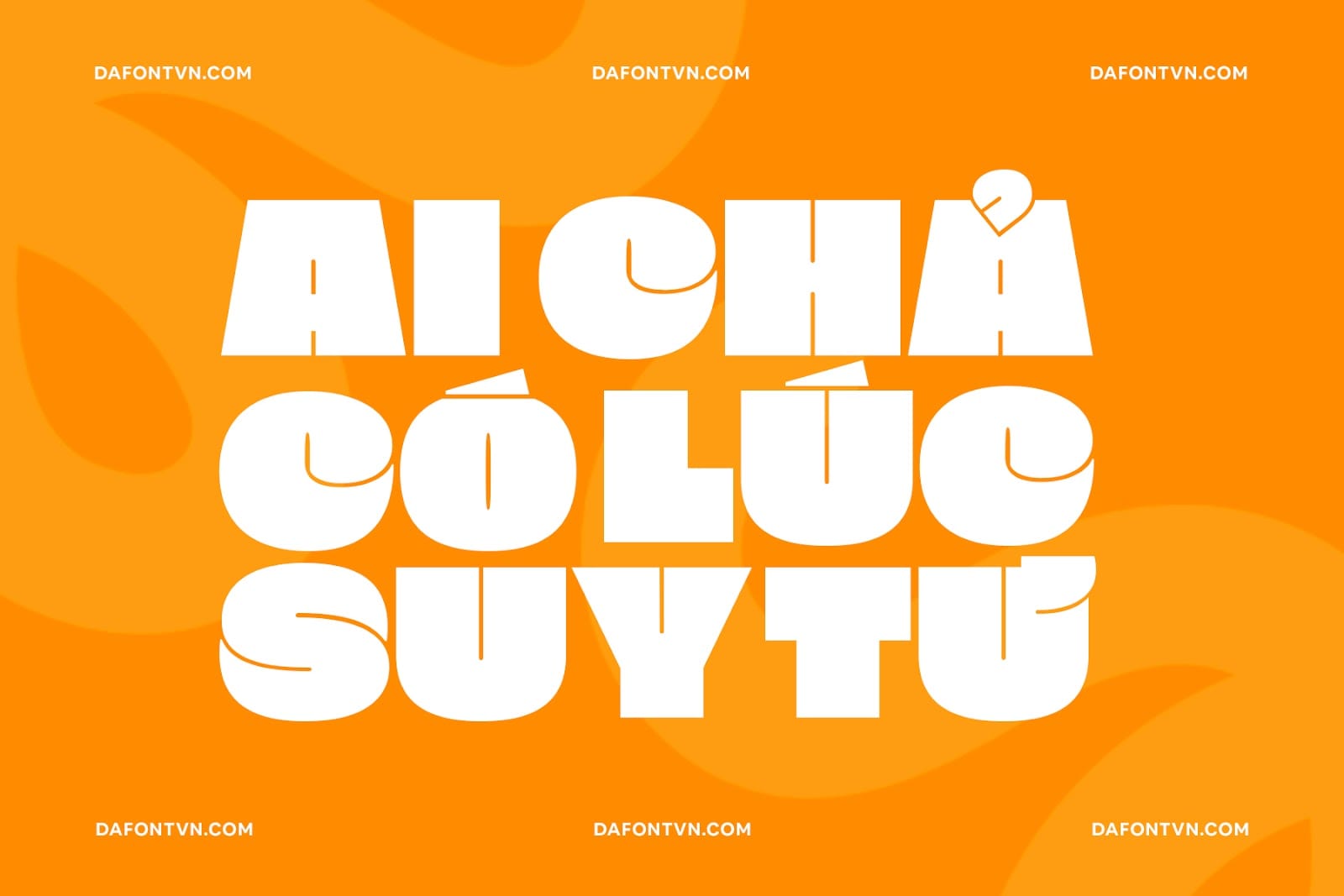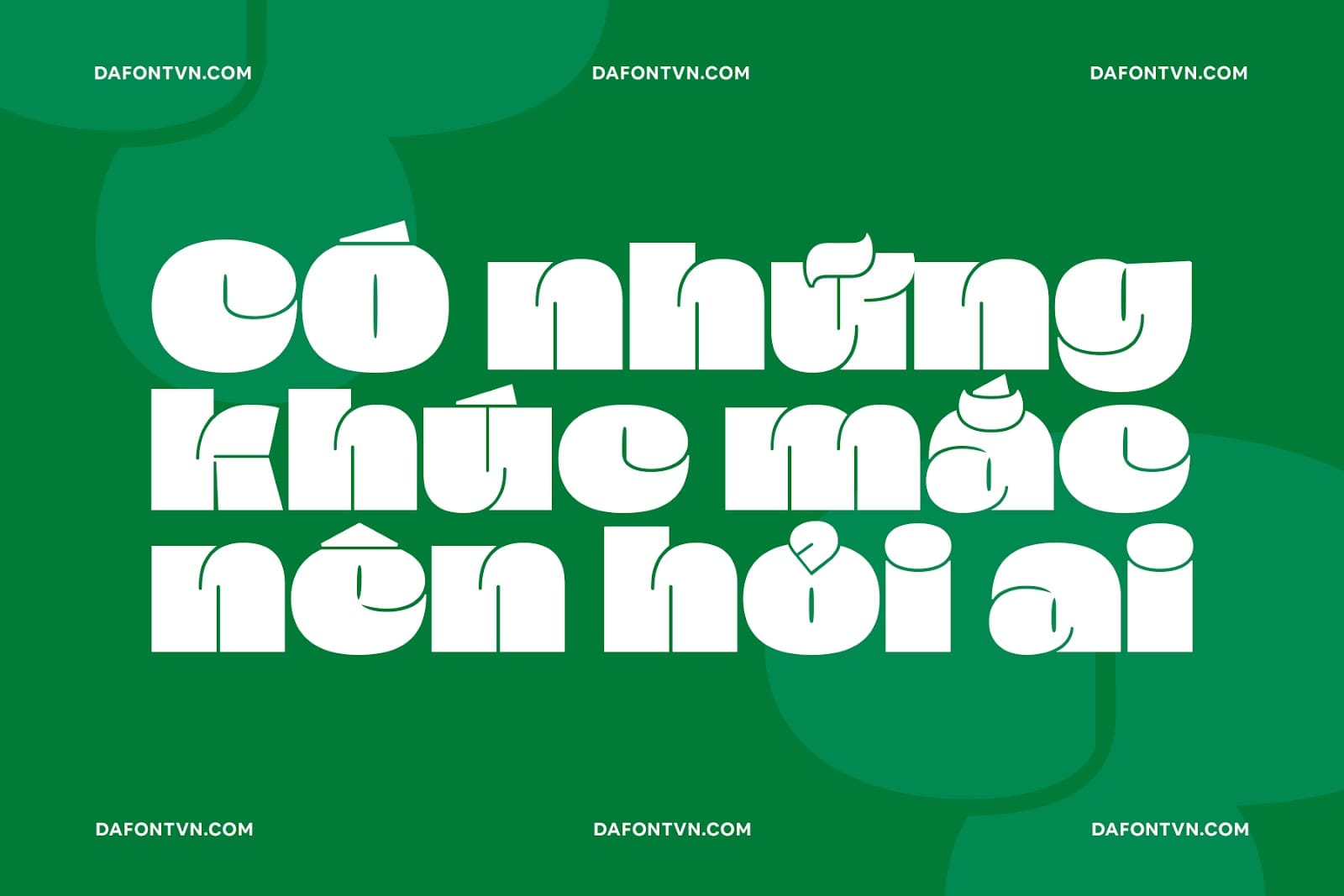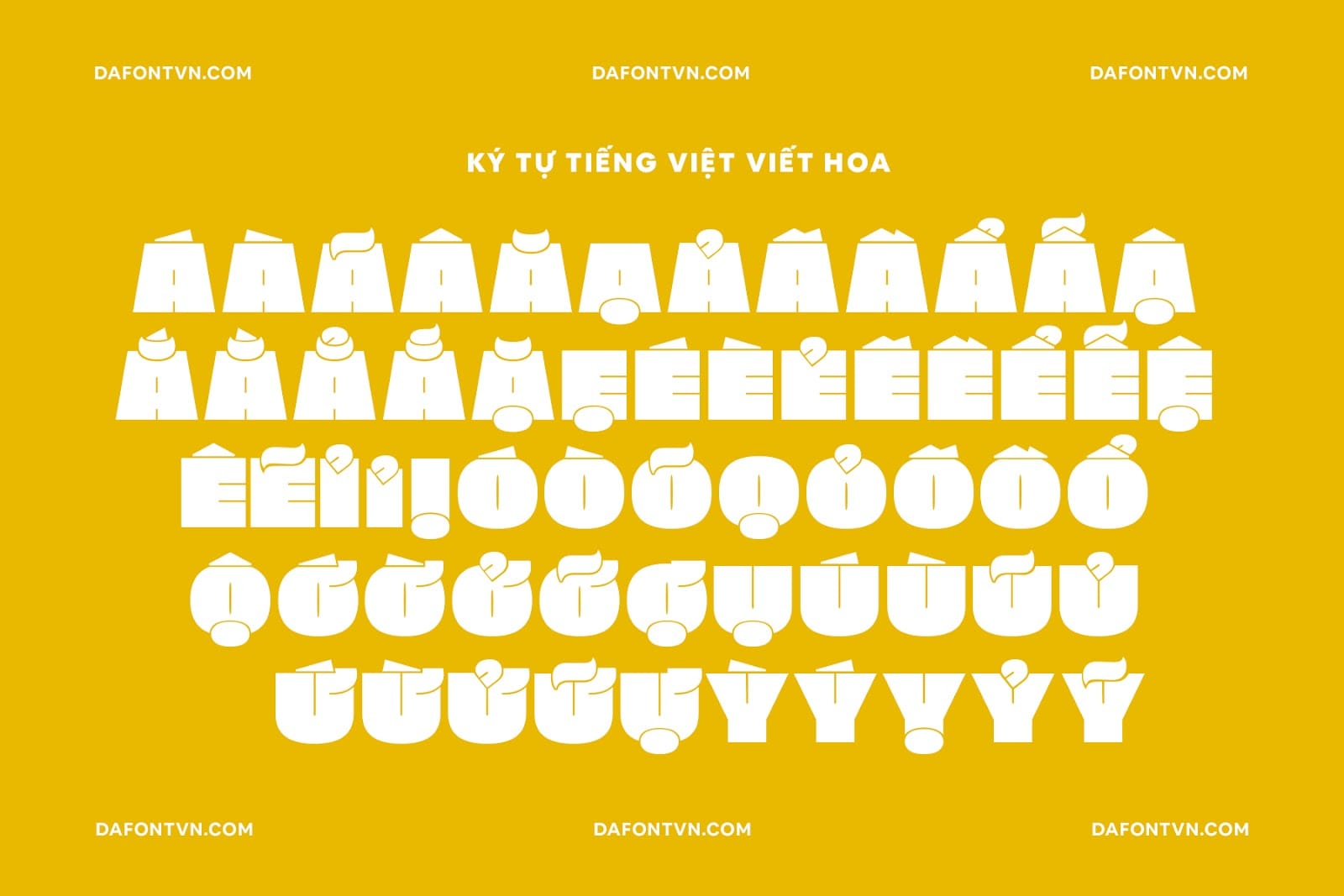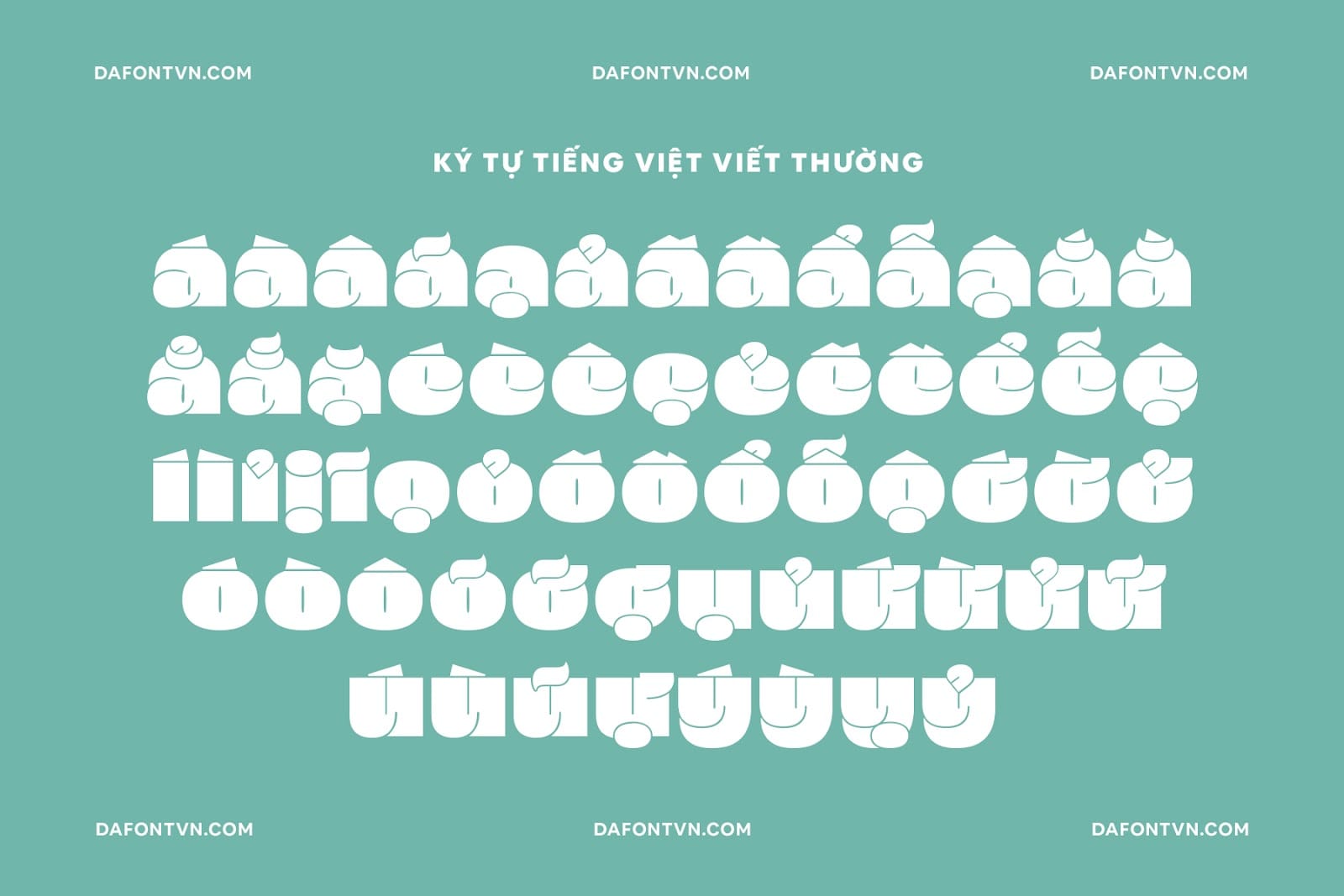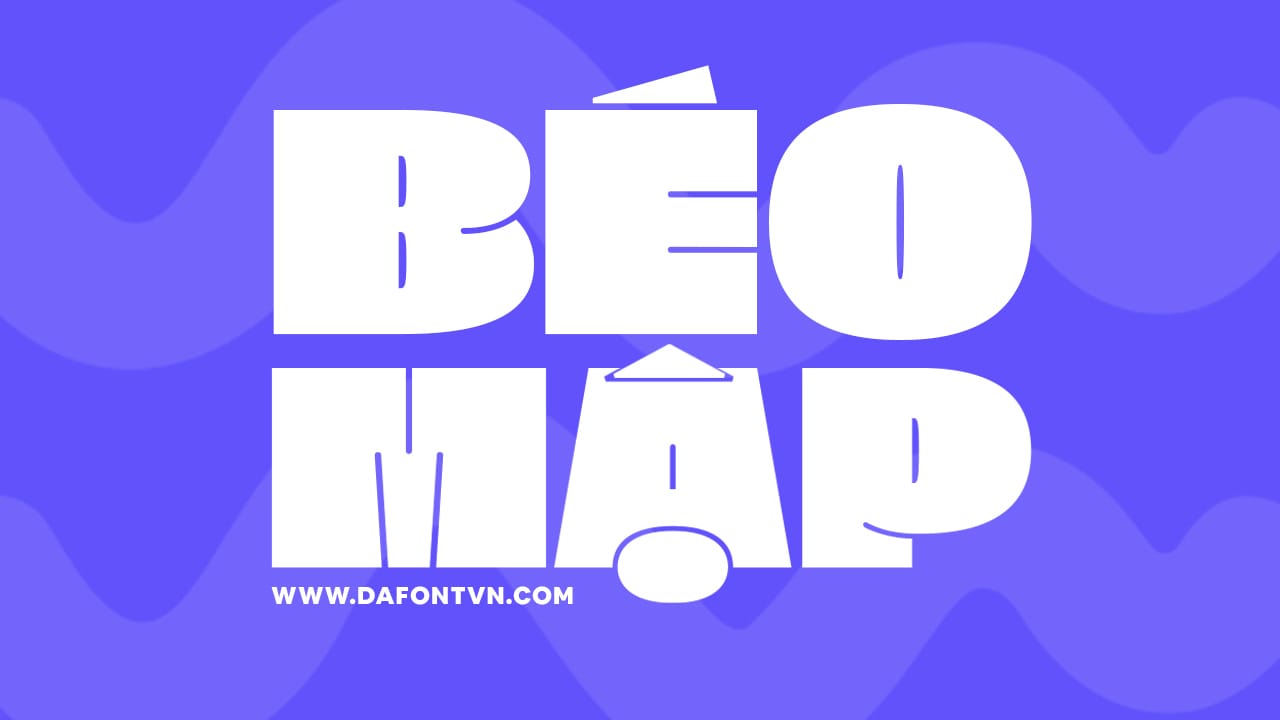
Fat Black – 1 kiểu font chữ hiển thị với độ dày đậm vô cùng ấn tượng. Fat vượt xa mọi ranh giới bằng cách bao hàm không chỉ một mà cả hai hệ thống chữ viết: tiếng Latin và tiếng Nhật. Sự kết hợp này cho phép bạn kết hợp liền mạch các ngôn ngữ khác nhau.
Mỗi chữ cái đều cực kỳ dày đặc đến mức thu hút sự chú ý ngay lập tức. Nhưng nó không dừng lại ở đó. Các chữ cái có khía cạnh ba chiều, với các phần tử như thân phải của chữ ‘n’ kéo dài ngay phía trên thân trái hoặc phần dưới của ‘z’ kéo dài về phía trước phần còn lại của chữ cái, tạo ra hiệu ứng trực quan sống động. Hiệu ứng 3D này cho phép các chữ cái được in đậm nhất có thể.
Ngoài ra, các điểm nhấn trong Fat được lồng ghép liền mạch vào từng chữ cái, tạo cảm giác về khối lượng và cho phép sử dụng không gian một cách hiệu quả, nâng cao thiết kế tổng thể của nó. Sự kết hợp độc đáo của các điểm nhấn này làm tăng thêm sự khác biệt và hấp dẫn về mặt hình ảnh cho Fat.
Ngoài các dạng chữ quyến rũ, Fat còn cung cấp nhiều loại mũi tên, chữ tượng hình và biểu tượng cảm xúc. Từ các biểu tượng cờ vua đến biểu tượng chơi bài, những yếu tố bổ sung này thậm chí còn mang đến nhiều khả năng sáng tạo hơn. Cho dù bạn cần truyền đạt một thứ gì đó làm điểm nhấn, ý nghĩa hay thêm chút thú vị, Fat đều có thể đáp ứng được. Trải nghiệm sự kết hợp độc đáo giữa trọng lượng cực lớn, tinh tế, khả năng bao phủ chữ viết linh hoạt và các yếu tố biểu cảm của Fat.